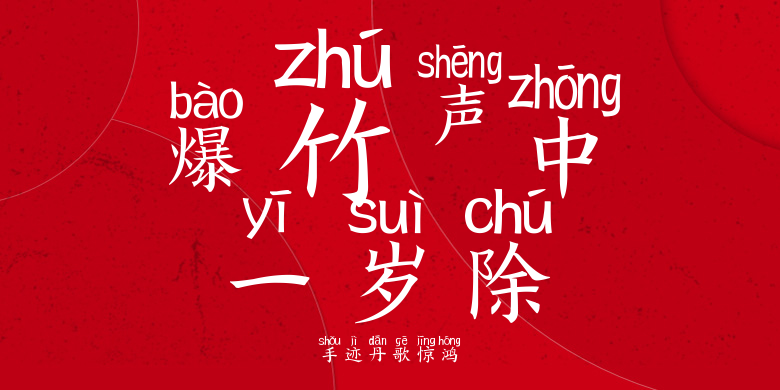
手迹丹歌惊鸿
手迹丹歌惊鸿,这款字体结构工整、笔画清晰,兼顾美观与易读性,适用于标题、正文、海报、包装、LOGO 等多种场景。字形优雅稳定,风格百搭耐看,适配日常排版与创意设计,让文字呈现更舒适、更具质感。手迹丹歌惊鸿一笔一画,皆是细节,以均衡的比例、流畅的线条打造舒适视觉体验,字形端正大气,风格简约现代。无论是商业设计、品牌宣传还是日常排版,都能轻松驾驭,让文字更有格调与力量。手迹丹歌惊鸿字体下载。